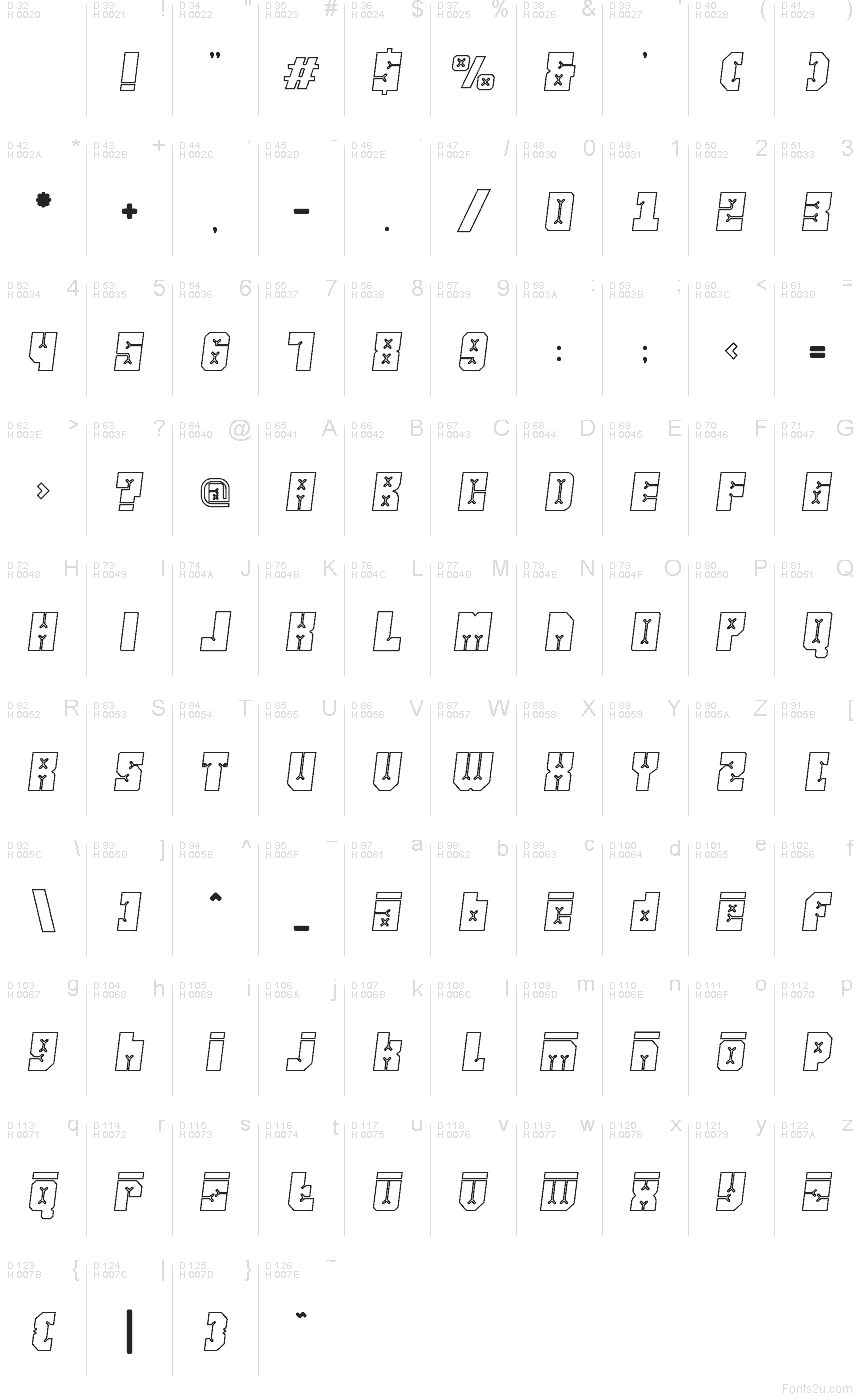
Friez Seven od Putracetol Studio je bezplatné konturové písmo typu display, jehož široké, dopředu nakloněné tvary působí dojmem, že jsou vyřezány z masivních panelů, nikoliv jen nakresleny jako běžná písmena. Malé šipkovité vnitřní prvky se v celém designu opakují a dodávají písmu osobitý rytmus, díky kterému nepůsobí velké siluety plochým nebo čistě geometrickým dojmem.
Tato kombinace výrazných blokových obrysů a opakujících se vnitřních akcentů skvěle funguje na plakátech, obalech alb, letácích, konceptech log či v záhlavích na sociálních sítích. Krátkým titulkům dodává dekorativní šmrnc bez nutnosti dalších ilustrací, zejména v layoutu, který cílí na grafický úder v duchu 70. let namísto neutrálního stylu nadpisů.
Friez Seven